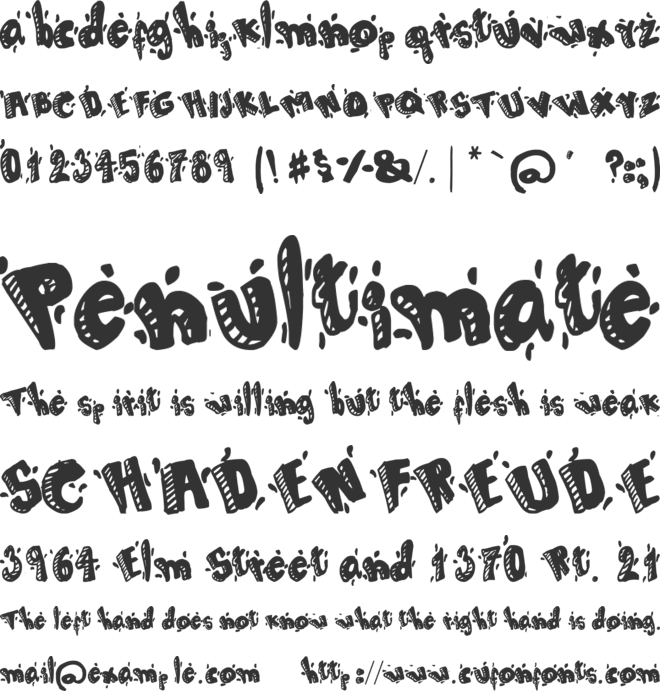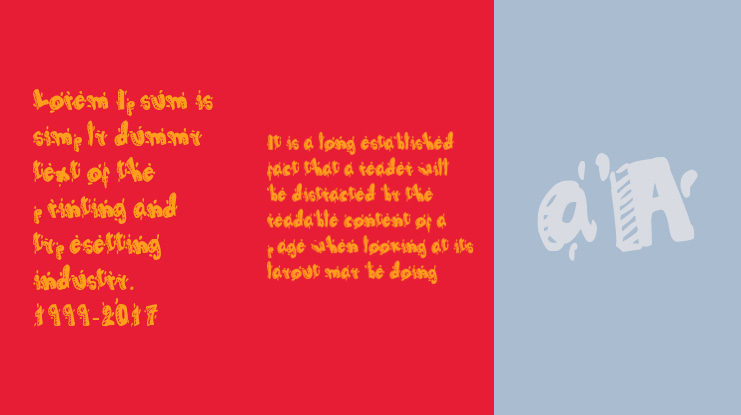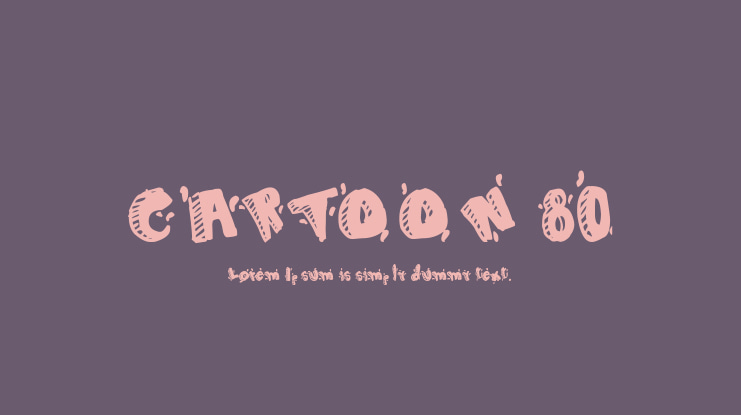
CARTOON 80 Font
espero que las disfrutes gracias por usar mis tipografías créeme no fue tarea fácil crearlas estas tipografías esta inspirada en aquellas caricaturas viejas de los años 80 y en especial en felix el gato son perfectas para el uso en carteles o como aplicación en camisetas etc disfrútalas